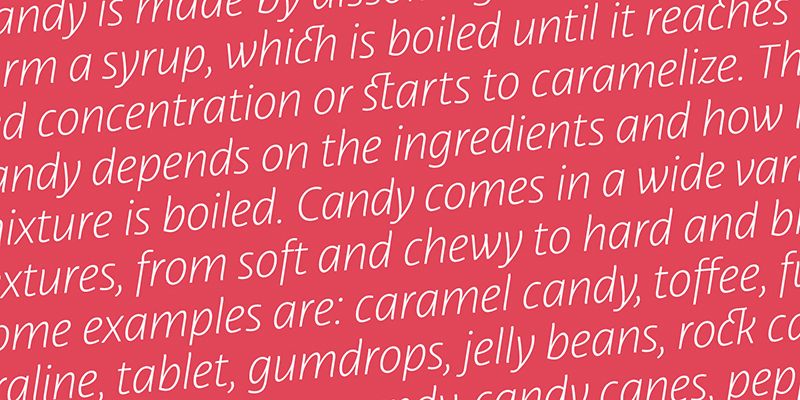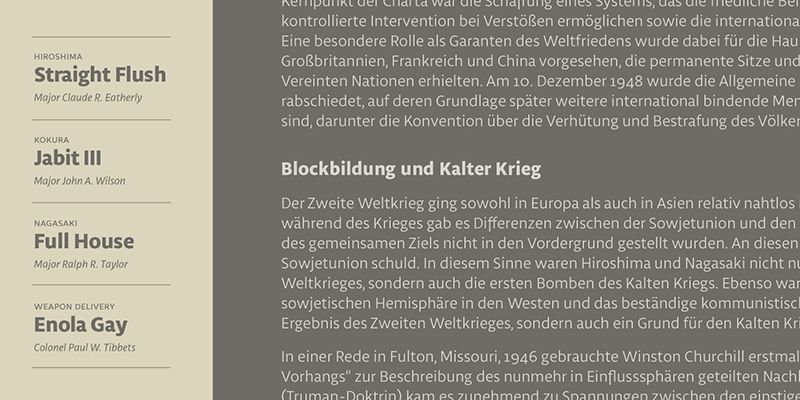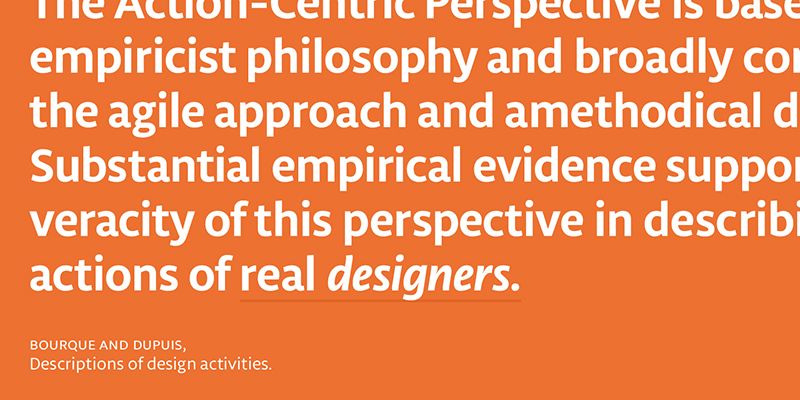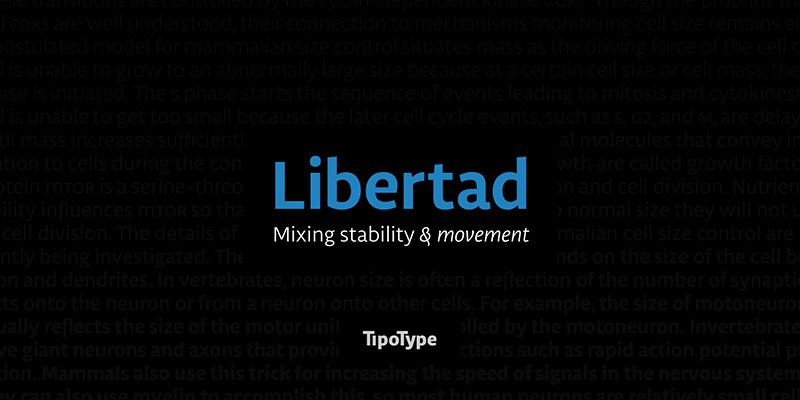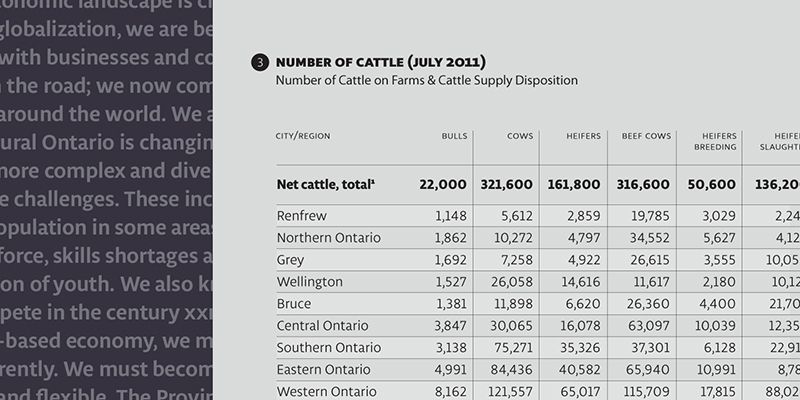
Libertad es un tipo de letra sans-serif que mezcla modelos humanistas y grotesque. Su característica más interesante es la combinación de regulares equilibradas con cursivas dinámicas, lo que la convierte en una fuente muy versátil para diferentes usos.